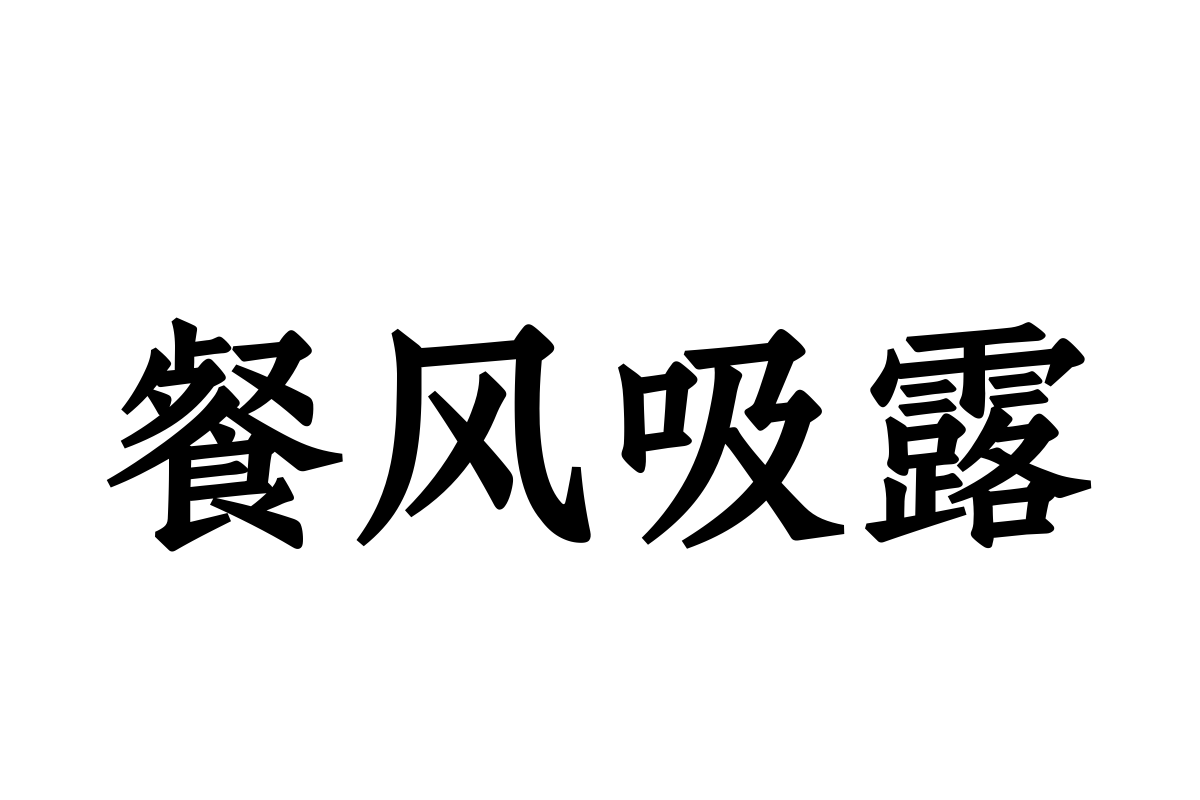
汉仪书仿85s是一款现代中文字体,由汉仪字库设计制作。这款字体具有独特的风格和特点,适用于各种印刷品和数字媒体。
1. 设计风格:汉仪书仿85s的设计风格简洁大方,线条流畅,具有较强的视觉冲击力。字体结构紧凑,笔画粗细适中,给人一种清晰、易读的感觉。
2. 字形特点:这款字体的特点是字形规整,每个字符都严格按照标准进行设计,确保在不同尺寸和比例下都能保持良好的视觉效果。同时,字体中的笔画粗细变化丰富,既有粗犷豪放的笔触,又有细腻柔和的线条,给人以丰富的视觉体验。
3. 适用场景:汉仪书仿85s适用于各种印刷品,如报纸、杂志、书籍、海报等。此外,这款字体也适合用于数字媒体,如网页、手机屏幕、电子广告牌等。无论是在传统媒体还是数字媒体中,汉仪书仿85s都能展现出其独特的魅力。
总之,汉仪书仿85s是一款功能强大、适用范围广泛的现代中文字体。无论是在印刷品还是数字媒体中,它都能为人们带来清晰、易读的阅读体验。